很酷的字体来画:玩得开心手工刻字
已发表: 2022-09-07寻找很酷的字体来绘制是与手写字体艺术相得益彰的最佳方法之一。 虽然可以公平地说,如今有很多很棒的软件工具可以帮助您创建终极版式,但发现不同的字体来绘制可以为您提供全新的技能。
手写字体是许多图形艺术家以及品牌设计师和排版专家的做法。 毕竟,如果没有一些绘制自己字体的技巧,你怎么能创建一些世界领先品牌使用的自定义字体呢?
今天,我们将帮助您开始进入手写字体的美妙世界的旅程,提供多种酷字体供您绘制和练习。
为什么要找到很酷的字母字体来绘制?
平面艺术家和品牌设计师可以使用许多资产来帮助他们为当今的客户创造终极设计。 您甚至可以找到一些工具来帮助解决字距调整和前导(字母之间的空格)等问题。
但是,学习如何手工绘制字体仍然有好处。 手写是许多创意专业人士实践的一项技能,尤其是那些专门设计公司标志的人。
通过手写字体,您可以学习如何从头开始制作令人惊叹的字体——非常适合您想为客户创建独特的设计。
用一系列不同的字体来练习书法可以帮助你敞开心扉去设计排版的创意过程。 这也意味着在向客户展示潜在的品牌设计时,您可以利用更广泛的技能。
让我们深入研究一些最好的字体来绘制以磨练您的技能……
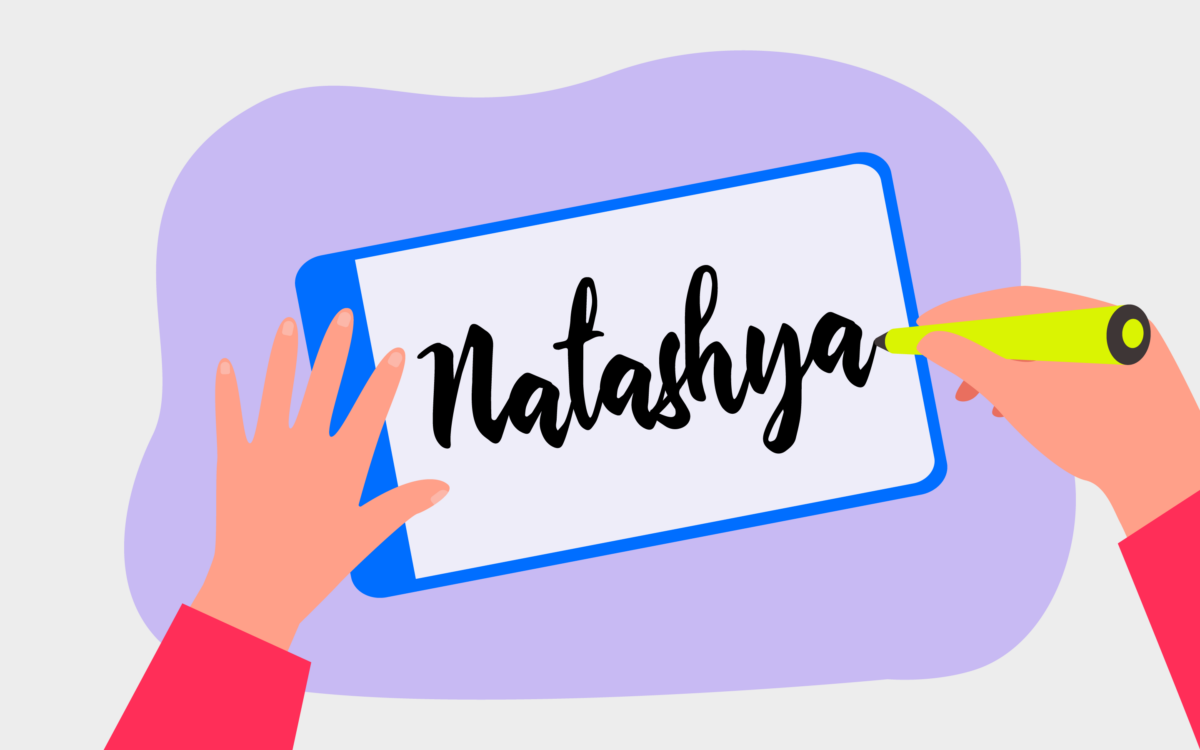
1.娜塔莎
Nataysha 是前卫和优雅的完美结合,是一种有吸引力的画笔式字体,非常适合许多标签、信头、海报等。 这种酷炫的手绘字体具有独特的异国情调,使其非常引人注目且具有原创性。
您甚至可以使用流畅的草书风格练习组合各种大小写字母。
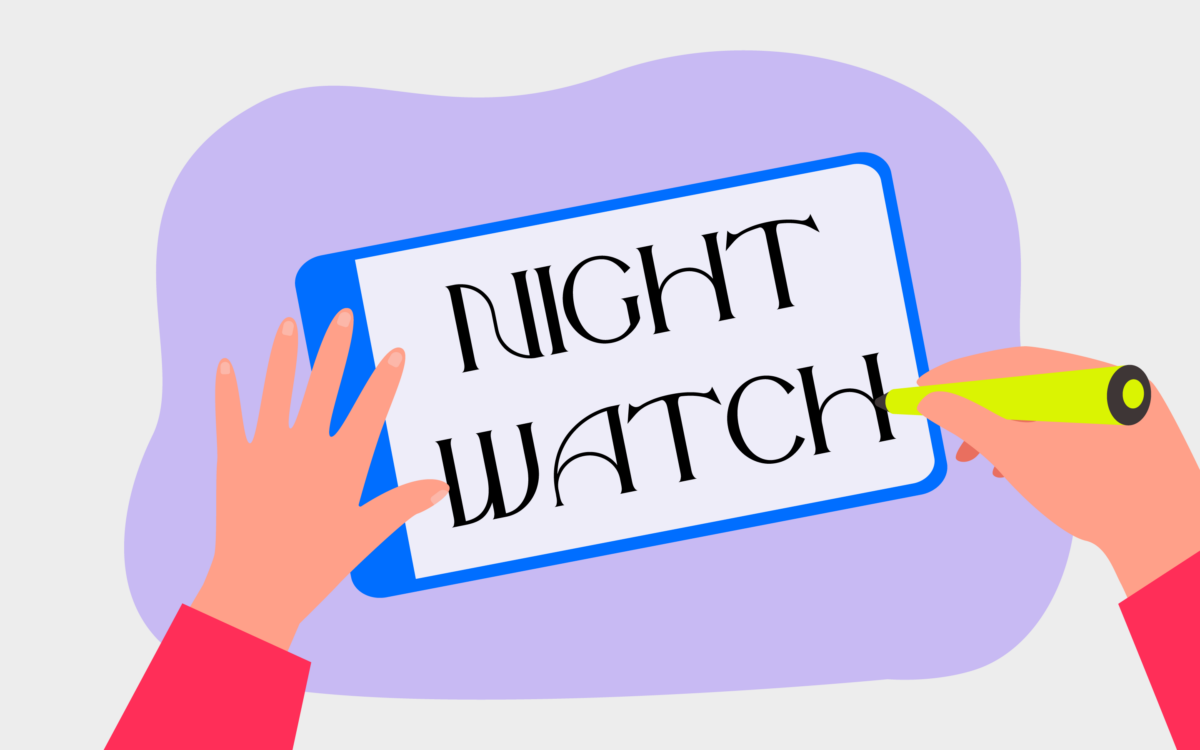
2. 守夜人
免费下载,The Night Watch 是我们绘制的酷字体列表中的绝佳选择。 Night Watch 非常适合短文本、标题和徽标,将大胆的衬线元素与圆形形式相结合,营造出引人注目的现代风格。
这种字体具有幻想和神秘的元素,使其成为一系列品牌的理想选择。
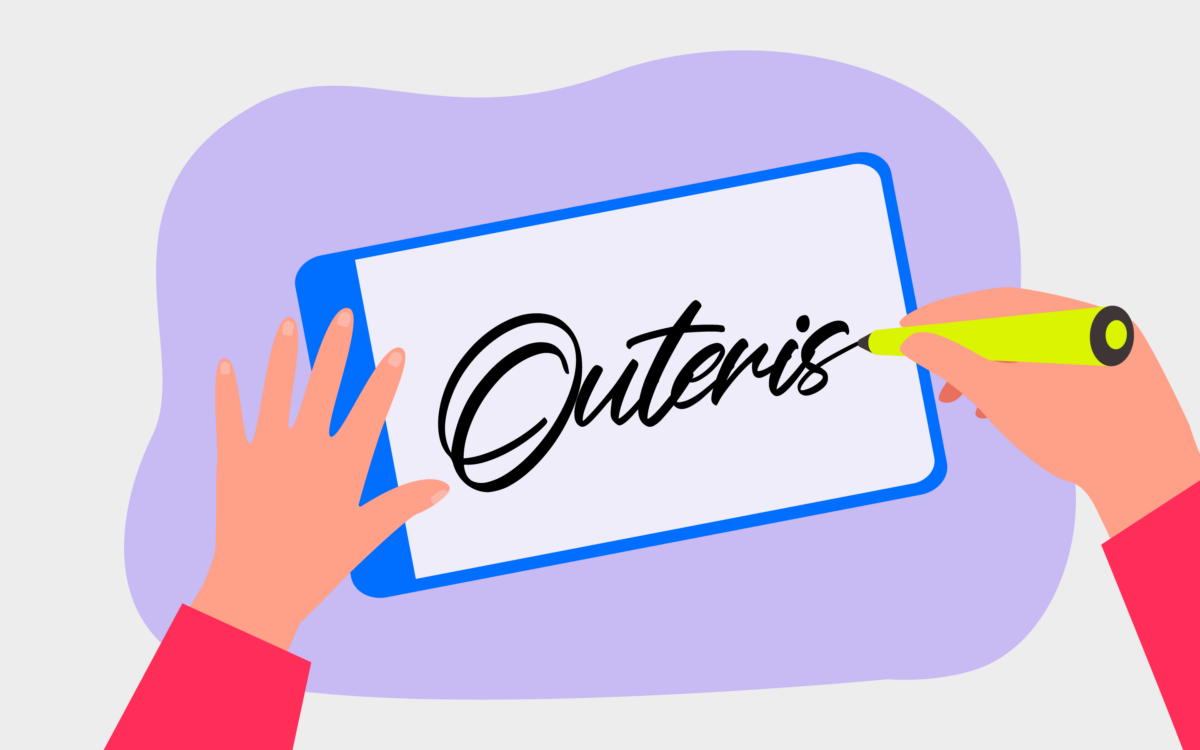
3. 外层
书法风格的字体“Outeris”充满活力和俏皮。 这种漂亮的字体让您注意到每个字母的独特曲线和华丽,非常适合学习如何绘制字体。
如果你用画笔画画,长而宽的笔触也是一个很好的选择。
4. 监听器
Snoofer 是一种未来派风格的手写字体,专为现代设计而设计,当您想用大胆而有趣的东西吸引眼球时。 Snoofer 字体间距精美,因此非常适合清晰,如果您无法找到既醒目又易于阅读的内容。
如果您正在为一家当代公司设计,这可能是一个很棒的很酷的字体。
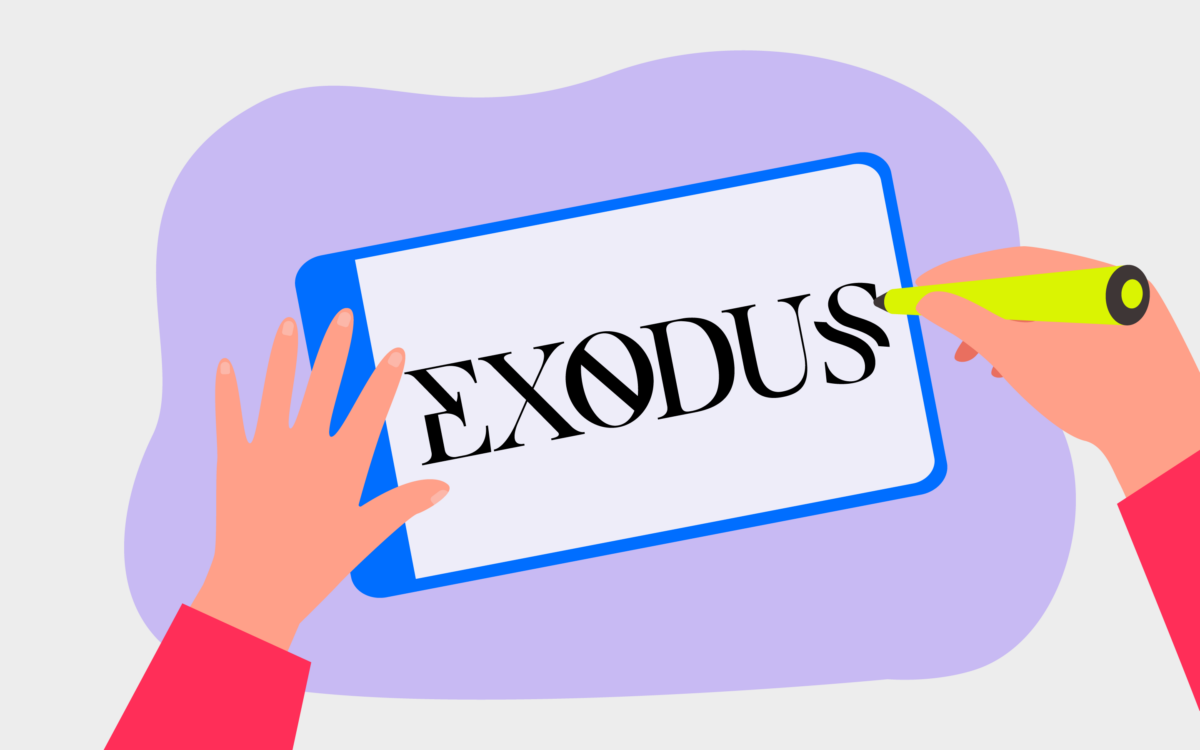
5. 出埃及记
Exodus 字体功能强大且引人注目,是一种漂亮的显示衬线字体,有一系列独特的替代字符可供尝试。 这种字体具有外星元素,以及模板样式的变化,因此您可以尝试不同类型的手写字体。
对于任何想要打破常规的品牌来说,这种排版可能是一个理想的选择。
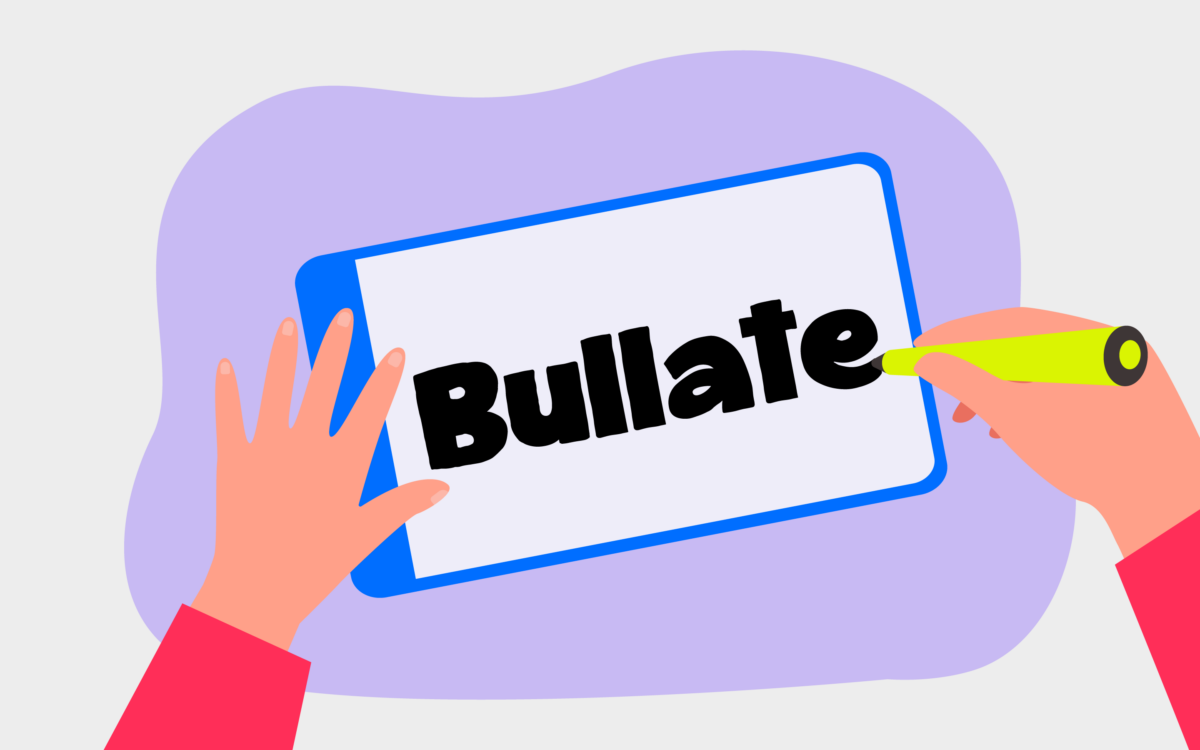
6. 吹牛
Bullate 字体是一种粗体、块状和自信的字体,非常适合具有友好优势的现代品牌。 无衬线字体使这种字体非常平易近人,非常适合受众较年轻的公司。
这种字体有很多有趣的曲线,这使它看起来不像今天可用的其他一些粗体字体选项那么激进。
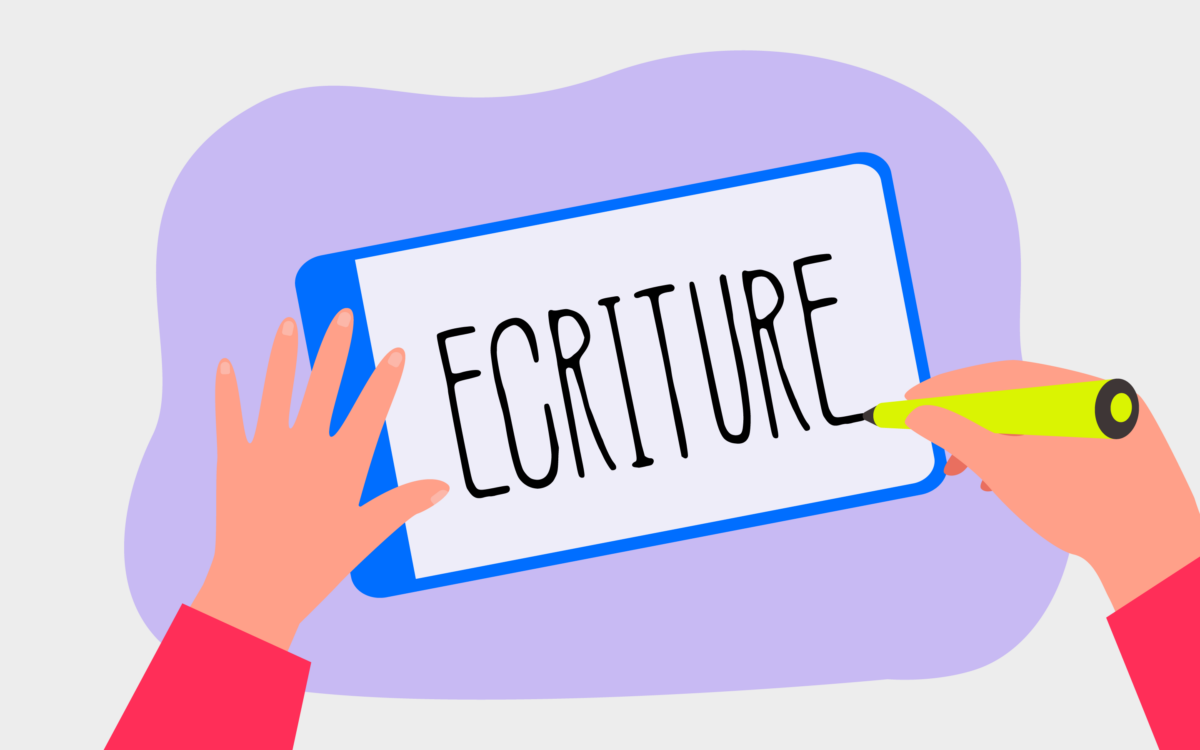
7. 书写
找到不同的字体来绘制并不一定意味着要始终如一地尝试复杂的书法风格的字体。 你也可以尝试一些更简单、极简的字体,比如 Ecriture 类型。
优雅而现代,这种字体具有时尚和时尚的美感,非常适合任何寻求斯堪的纳维亚风格品牌美感的人。
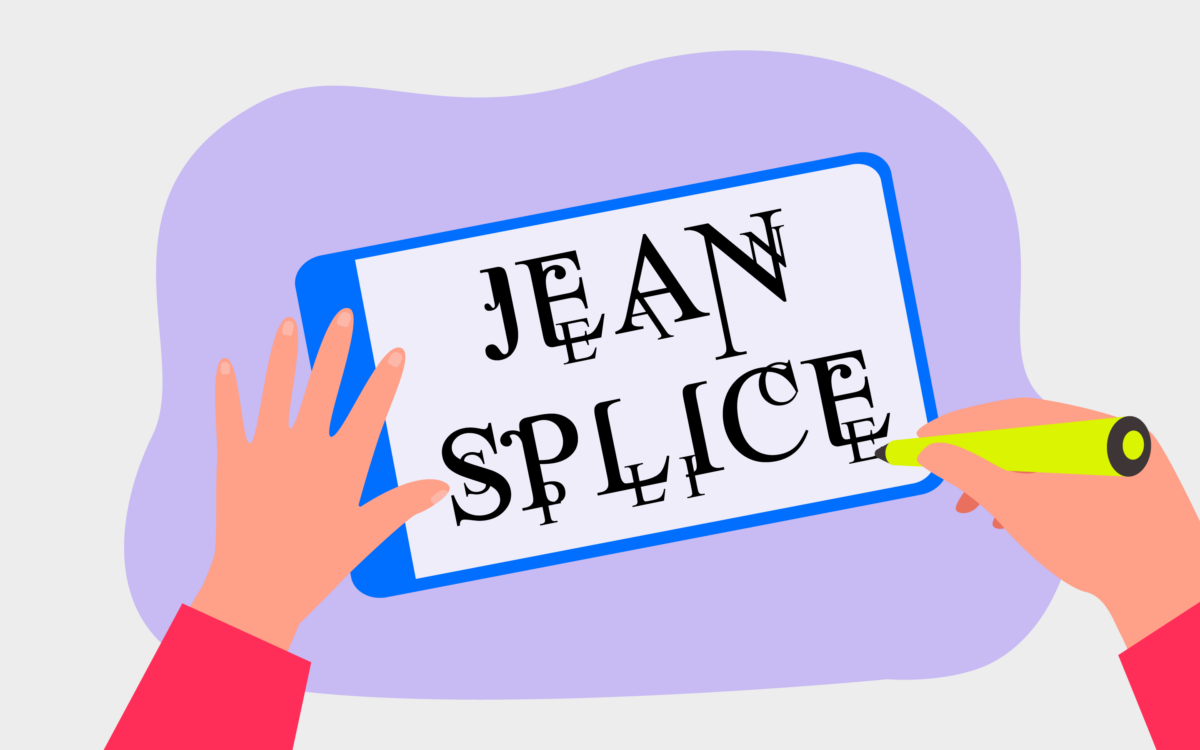
8. 让·斯普利特
Jean Splice 是一种让您忍不住盯着看的字体,它具有幻想和科幻的吸引力,使其成为此列表中针对特定受众的较酷字体之一。 该设计涉及将相同字体的多种不同尺寸组合到一行中,以创造艺术效果。
这是电影公司的好字体,甚至是书籍封面。
9. 鹪鹩
一种有趣且本质上很酷的字体,Wren 使用字母中的空白来创造一些非常独特的东西。
这款字体拥有许多粗线条和细条纹,一定会激发您的想象力,让您思考现代字体和更传统字体的并置。
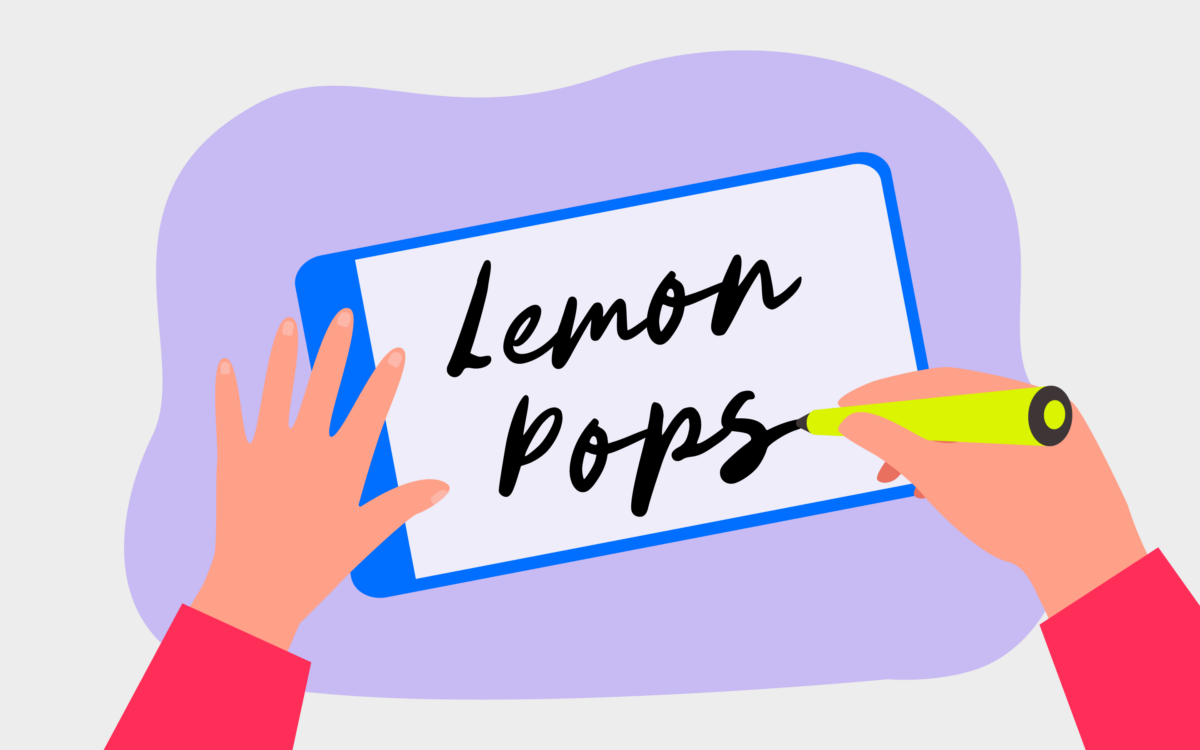
10. 柠檬汽水
Lemon Pops 非常适合吸引年轻观众的注意力,它是一种醒目的醒目字体,具有优美的手写氛围。 这是我们希望在为现代青少年设计的网站上看到的那种字体。
非常适合在您的手写字体项目中尝试不同重量的沙子纹理,这是添加到列表中的绝佳字体。
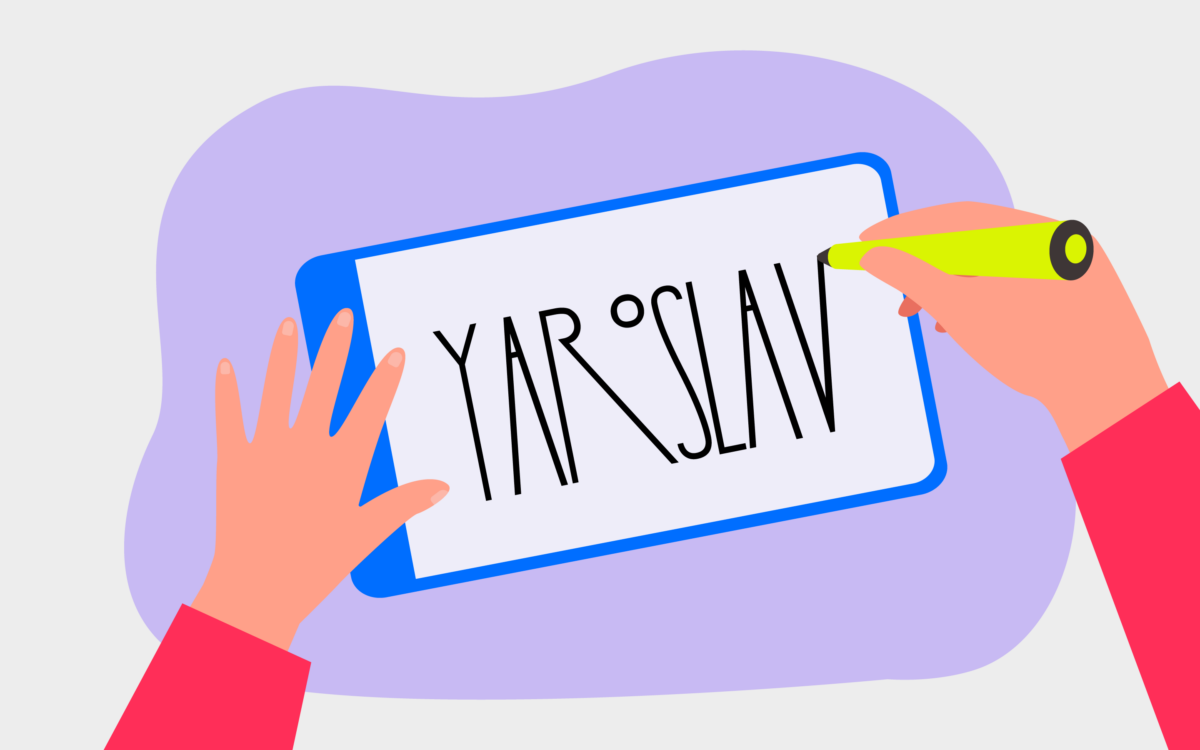
11. 雅罗斯拉夫
这种雅罗斯拉夫字体有一些奇妙的装饰艺术。 作为饮料品牌或餐厅品牌的一部分,肯定会吸引眼球,这种漂亮的字体结合了独特的间距和细长的线条,具有独特的视觉吸引力。
如果你喜欢练习一些窄字体的想法,这可能是你的选择。
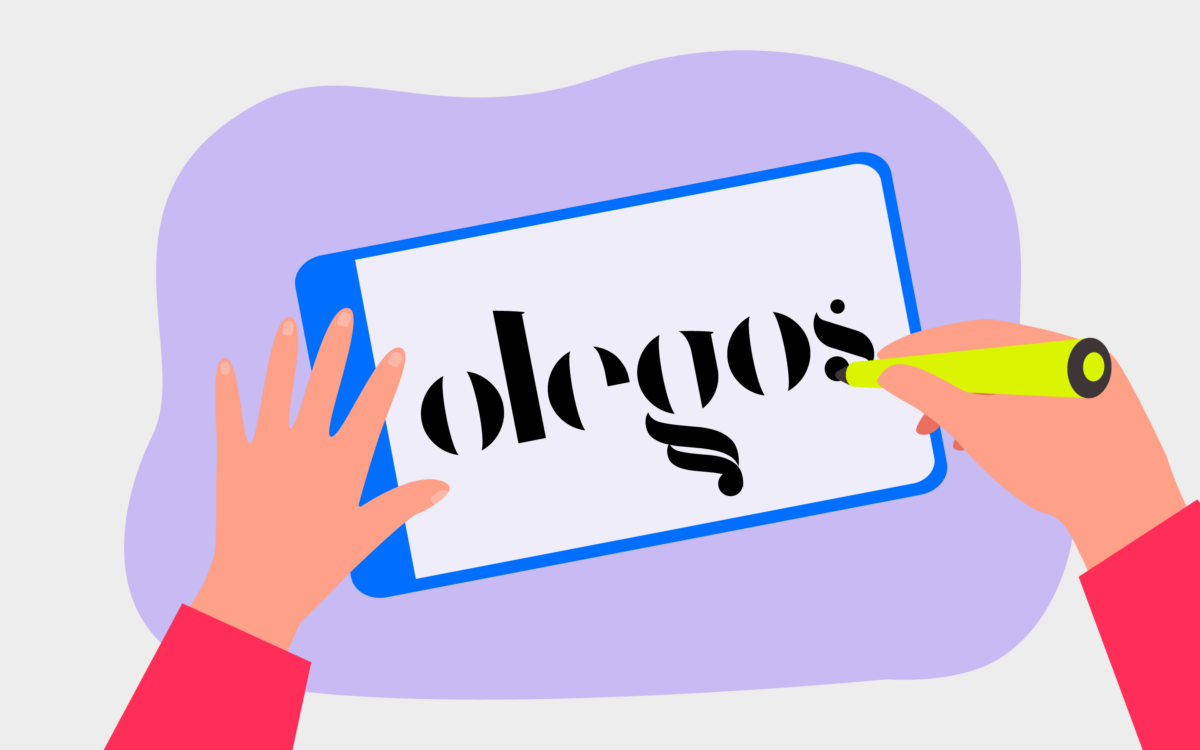
12. 奥乐高
Olegos 极简精美,是一种以斯堪的纳维亚风格为设计理念的字体。 这种字体是通过扩大各种字母之间的间隙而创建的,它促使人们自行改造字母。
这是一种让人们思考的好字体,它可能是开始练习手写字体技巧的绝佳方式。
13. 帕杰里托斯
如果您是手写字体世界的新手,Pajaritos 字体清新而年轻,是一种很好的尝试。 您可以考虑添加自己的装饰和元素,具体取决于您正在从事的项目类型。
我们还建议使用诸如字距调整和重量之类的东西,以查看字母在不同格式中的外观。
14. 滑板花花公子
简单而引人注目,这是我们绘制简单酷字体的首选之一。 Skater Dudes 字体是一种粗体、无衬线字体,有大写和小写两种。 这种类型,势必会吸引更年轻、更叛逆的观众。
我们喜欢快餐店的设计,或者对家庭和年轻观众具有强烈吸引力的类似设计。
15. 面包房
我们是这种酷字体古怪而年轻的本质的忠实粉丝。 Bakehouse 字体将一些传统的衬线元素与许多曲线和蓬勃发展相结合,真正使设计脱颖而出。
对于任何寻求更复古风格的排版来为其品牌推广工作的人来说,这种字体可能是理想的选择。 这种设计肯定有一些特别之处。
16. 文件夹
Folders 是一种俏皮的字体,具有一种美妙的优雅。 虽然不像我们要绘制的酷字体列表中的其他一些草书或脚本样式字体那么复杂,但它仍然具有引人注目的手写特性。
对于试图传达友好和脚踏实地的公司来说,这种字体可能会很好用。
17. 艾丽西亚
Elixia 简单但有效,是一种几何字体,专注于圆滑、简单的线条和角度。 据设计师 Kimmy Lee 介绍,这款字体具有很强的垂直元素,灵感来自六边形网格系统。
如果您要选择它作为绘制酷字体的首选,我们建议您随身携带一把尺子,以使线条尽可能笔直。
18.酷Unkle
Cool Unkle 结合了大胆的笔触和略微倾斜的设计,是一款功能强大的手写显示字体,您将立即学会如何绘画。 这种字体既引人注目又易于阅读。
这些字母完美和谐地结合在一起,非常适合在产品上写报价或设计独特的文字标记。
19.保加利亚文
如果您准备好在一段时间后使用手写字体更高级一些,Bulgaria Script 字体是一个不错的选择。 您可以使用这种装饰性字体上的粗体装饰和延伸线条来实现您想要的复杂程度。
绝对值得玩弄字体的重量,因为更苗条的视觉可以创造一种全新的美感。
20.独白圆润
古怪而令人兴奋的 Monologue Rounded 字体是您的首选,如果您想尝试在字母中调整大小以创造独特的效果。
这种字体有多种不同的变体,专注于在整个单词的各个点加长和缩短不同的字母,以创造视觉兴趣。
21. 紧身牛仔裤
如果您与时尚品牌或试图吸引年轻观众的公司合作,Skinny Jeans 是一个不错的选择,它是一种更简单的酷字体。 我们喜欢这种字体中的某些字母在正确使用时几乎可以融合在一起。
也绝对值得尝试大字母上的繁花。
22. 飞溅
Splash 字体现代而简约,采用粗体、粗线条和醒目的元素,真正吸引任何观众的注意力。 这种手绘字体具有年轻的性质,对于想要为年轻受众的品牌设计品牌标识的人来说,它是一个很好的选择。
练习这些字体以使用画笔或钢笔进行绘制不会有任何问题。